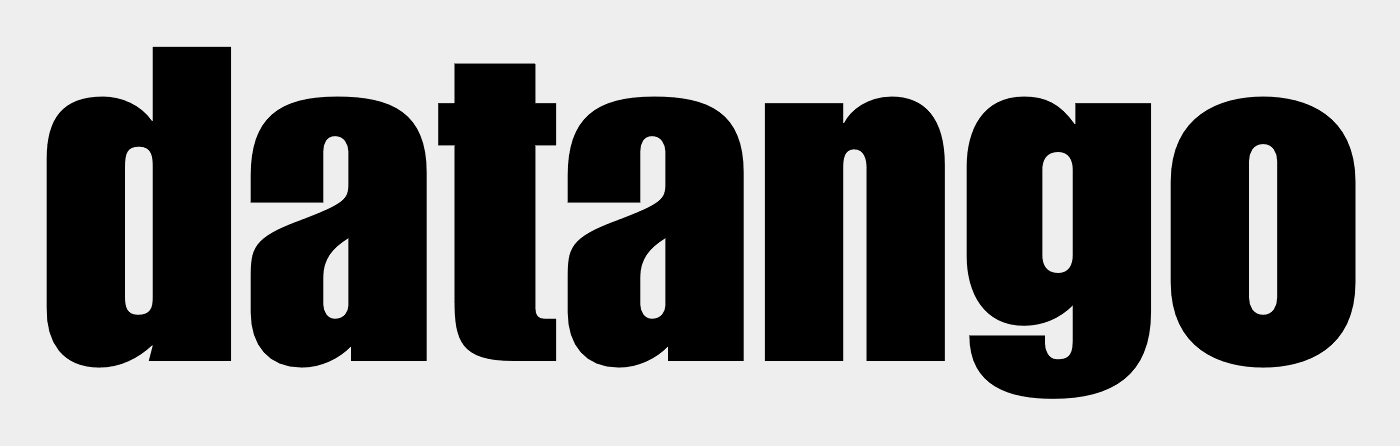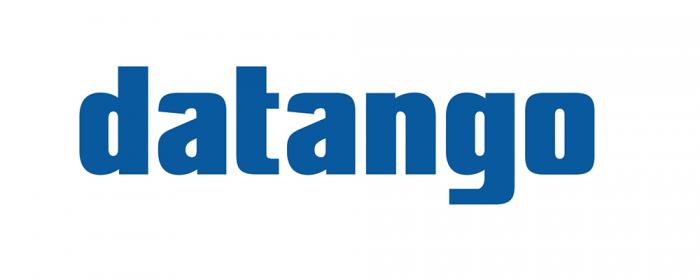
Schrift aus Logo gesucht: datango
ich suche die Schrift aus diesem Logo. Alles was whatthefont vorschlägt passt nicht. Ich denke es ist keine kaufbare Schrift, sondern eher ein Free-Font. Hat die jemand schonmal gesehen, kennt sie?
Cutting Edge Impact?!  :-?
Da ist es auchdurchaus möglich, das die 6 unterschiedlichen Buchstaben für das Logo direkt gezeichnet wurden
gemäß dem alten leitsatz: lieber schlecht selber gemacht als auf einen bestehenden font zurückgegriffen  :blabla:
Wie hast du das rausgefunden Bertel? Wieder erkannt? Oder gibt es außer whatthefont noch (gute) Schrift-Such-Möglichkeiten?
Nun, in diesem Fall war die Anfrage an menschliche Fonterkenner schon richtig, denn ist an den Buchstaben herumgezupft oder geschnitten, können den Ur-Font die Automaten nicht immer erkennem. Erkennt man, an welchen Buchstaben eindeutig etwas verändert wurde, die in der Font-Suchmaschine vom Vergleich ausnehmen, und auch oft mit nur wenigen unterschiedlichen Buchstaben suchen, da mehr Buchstaben eher die Trefferwahrscheinlichkeit verschlechtert, da dann eventuell abweichende  (veränderte) Buchstaben duie Auswahl ähnlicher gefundener Fonts eher einschränkt